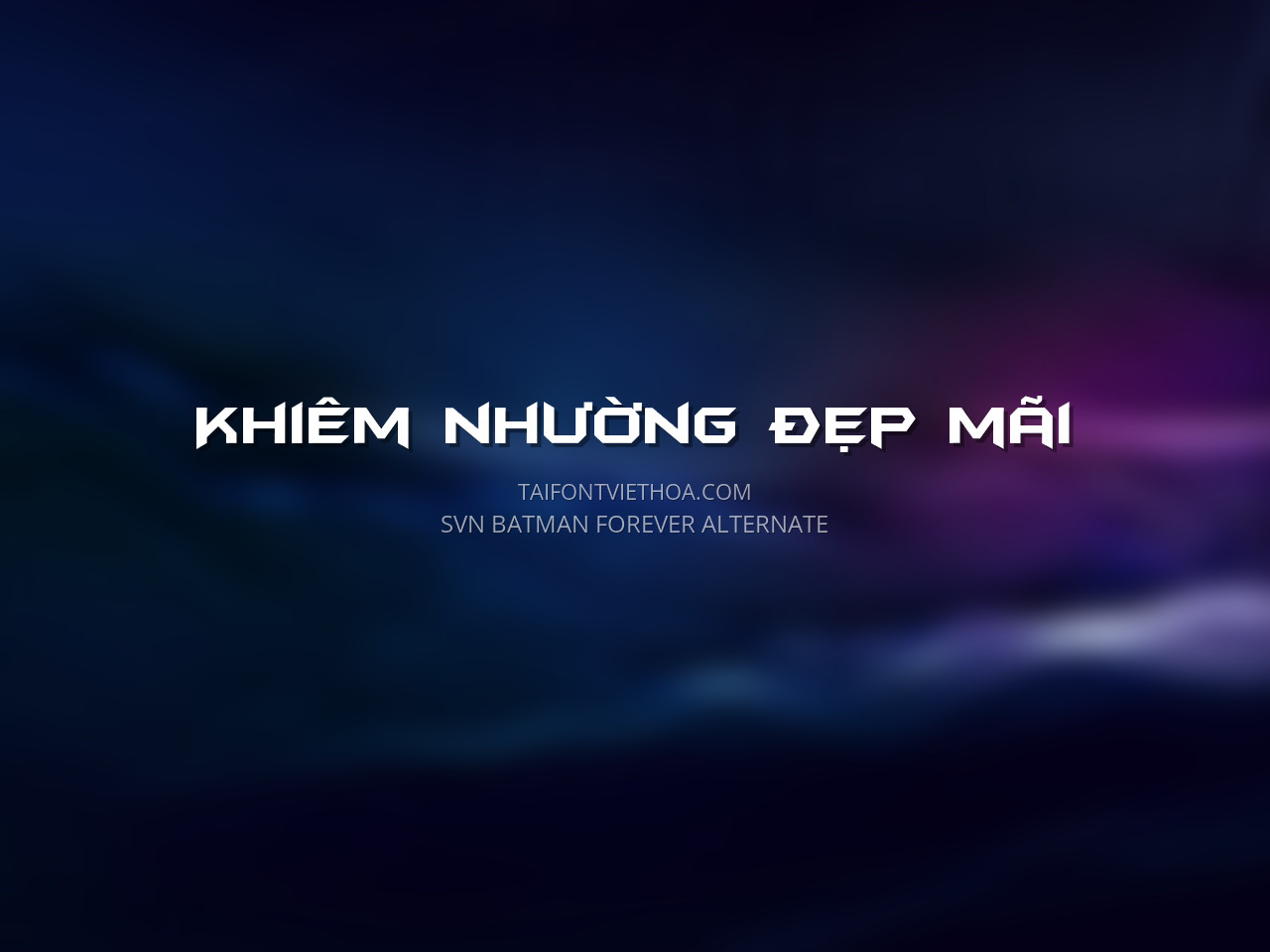
Giới thiệu về font SVN Batman Forever Alternate – Kiểu chữ sans-serif đậm nét, cá tính và hiện đại
SVN Batman Forever Alternate là phiên bản Việt hóa của font Batman Forever Alternate – một kiểu chữ sans-serif với thiết kế đậm nét, góc cạnh và rất cá tính. Font mang phong cách hiện đại, phù hợp cho các dự án thiết kế thương hiệu, quảng cáo, truyền thông kỹ thuật số và các sản phẩm giải trí.
Phiên bản Việt hóa của SVN Batman Forever Alternate đã được Taifontviethoa.com chăm sóc kỹ lưỡng, hỗ trợ đầy đủ dấu tiếng Việt cùng hơn 70 ngôn ngữ khác. Font giúp các nhà thiết kế dễ dàng áp dụng trong nhiều dự án đa dạng mà vẫn giữ được phong cách mạnh mẽ, trẻ trung và chuyên nghiệp.
Thiết kế sans-serif góc cạnh – Ứng dụng đa dạng trong thương hiệu và giải trí
SVN Batman Forever Alternate sở hữu các nét chữ sắc nét, dày dặn và cân đối, tạo cảm giác nổi bật và ấn tượng. Font rất phù hợp cho tiêu đề, logo, poster và các sản phẩm truyền thông cần sự cá tính và mạnh mẽ. Phong cách thiết kế của Batman Forever Alternate rất thích hợp với các dự án công nghệ, thể thao, quảng cáo và giải trí.